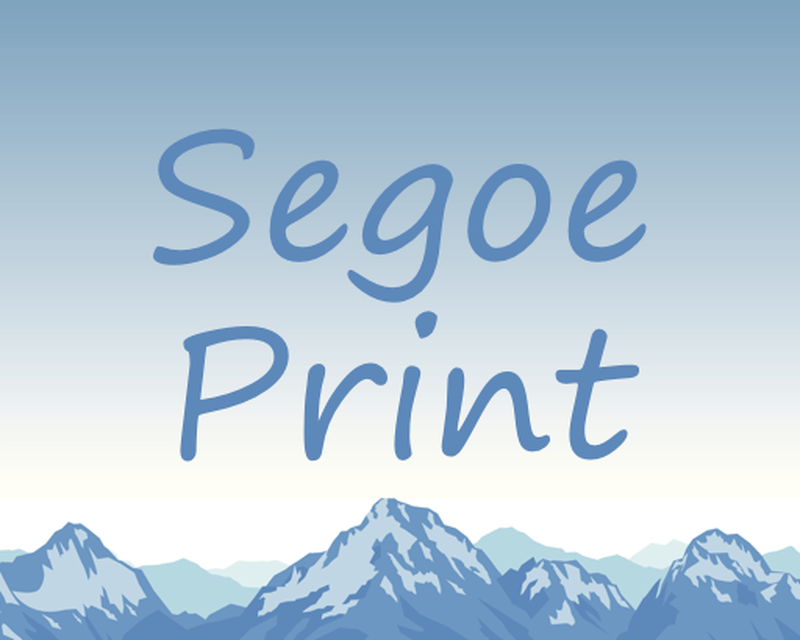
Заменяем шрифт Segoe в приложении «Записки»
Выбор шрифта в приложении Microsoft «Записки» по умолчанию не предусмотрен. Однако не всем по вкусу используемый шрифт Segoe, особенно, если требуется вывести информацию на печать.
С помощью небольшой уловки вы сможете изменить шрифт на более строгий. Кроме того, вы также сможете выбирать форматирование текста по своему усмотрению.
шрифты метрически несовместимы с Frutiger, поэтому не могут
использоваться в качестве заменителей. [6]
Включено 1 августа, 2006 г., Monotype Imaging объявила о приобретении Linotype у его материнская компания. Независимо от того, сигнализирует ли это о конце этого глава в истории шрифтов Segoe еще впереди. [7]